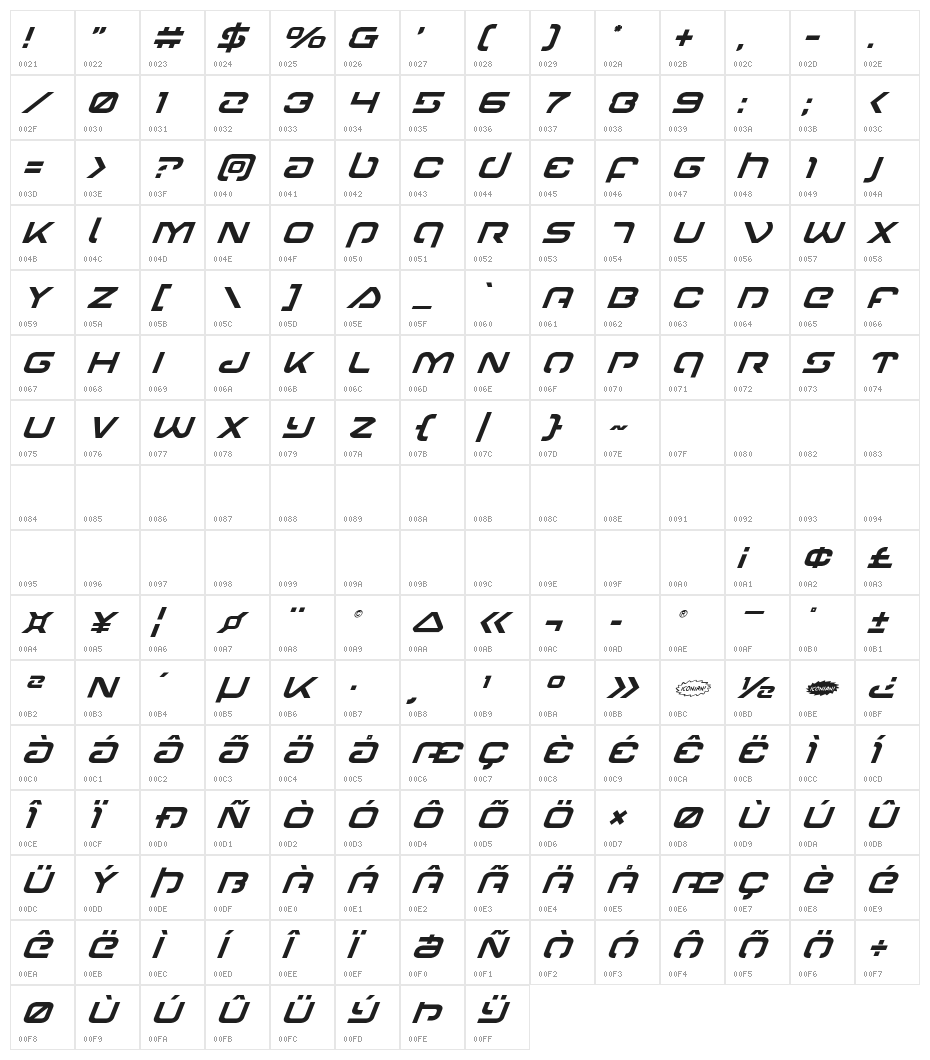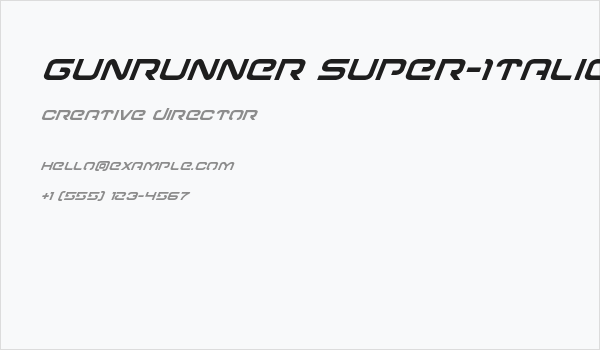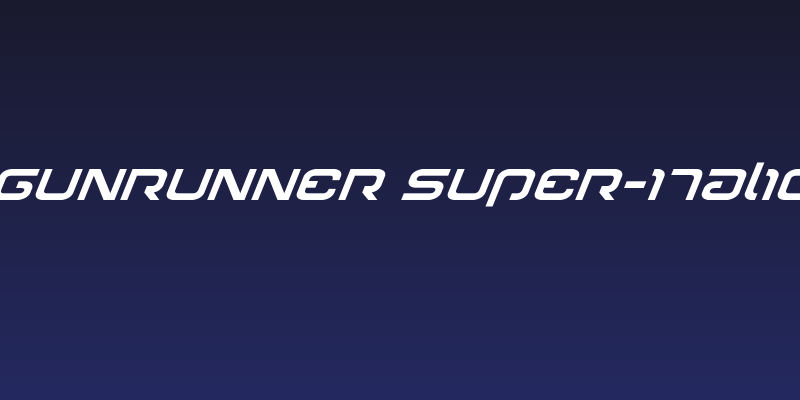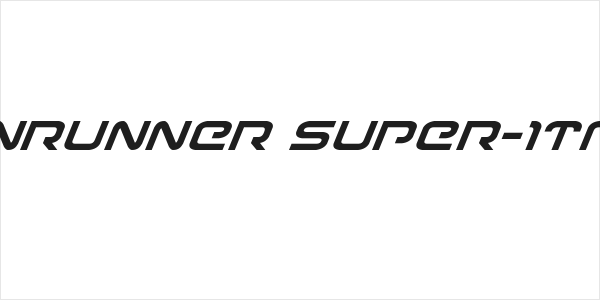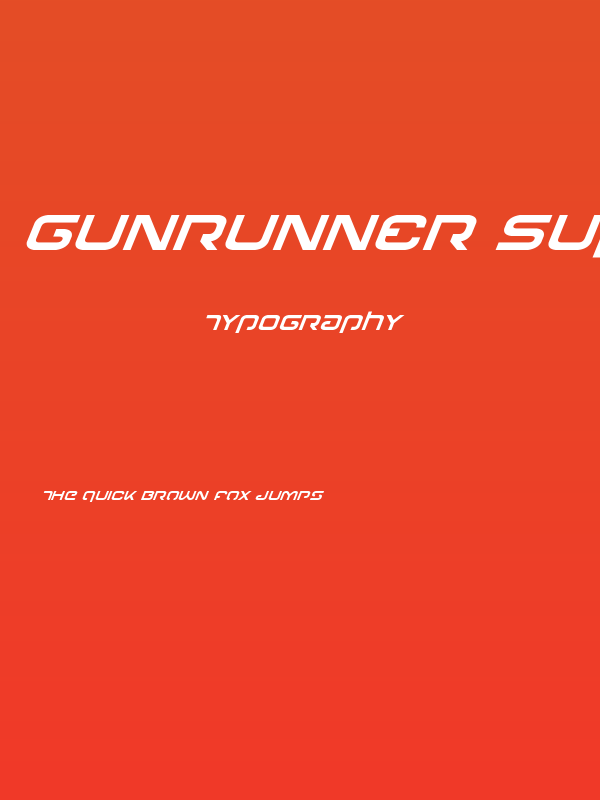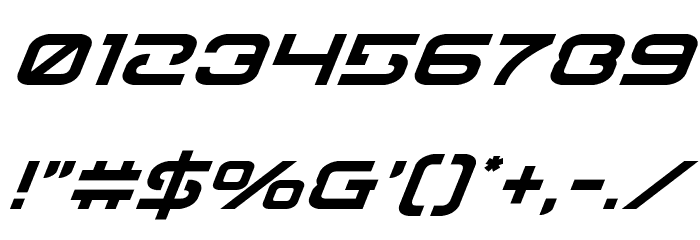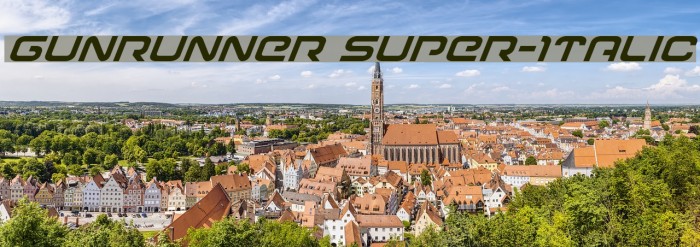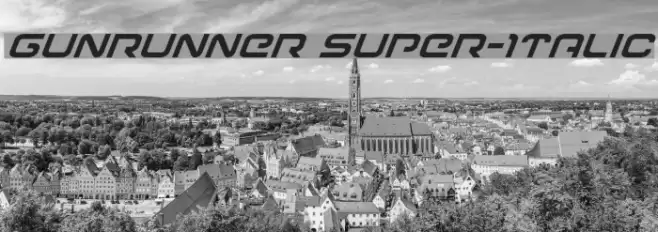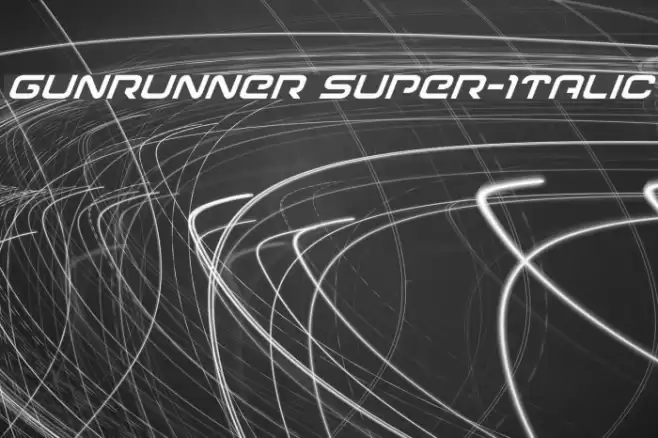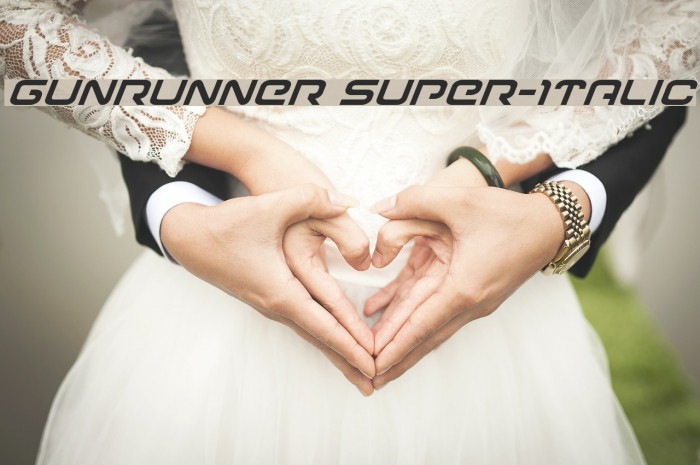
Gunrunner Super-Italic Font
| Proyectos propuestos | Ideal for projects that require a modern and edgy look, such as technology branding, video game titles, or automotive advertisements. |